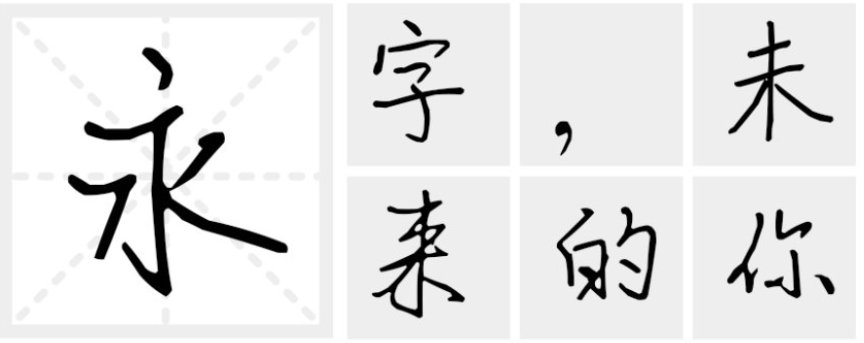
清秀隽丽的文字,一笔一划,骨络分明,结构均匀,充满的关心和疼爱;她也总是写上温暖的话鼓励他,笔画粗细一致,布局结构错落有致,字体中流露着纯真和快乐,透露出温馨感。
字体是能给人温暖的,可以悸动人的心灵深处
三极执子之手,执子之手,与子偕老。 结构严谨,笔触尖锐有力,风格明显,气质独特。一笔一划都诉说着一个美好又甜蜜的爱情故事,该款字体可广泛用于书刊、广告、包装、影视以及社交网络个性化用字